Modern Calligraphy Ink of Word Daylight
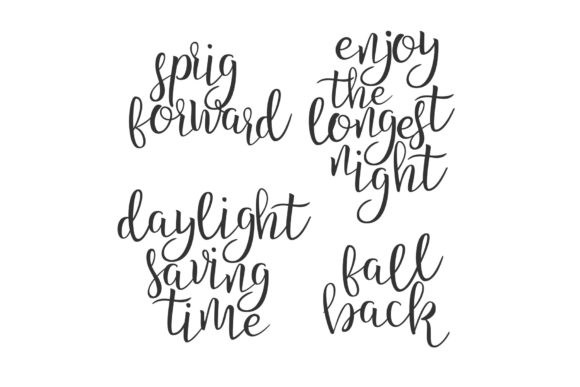
Пошук відповідних елементів дизайну може бути складним, але Modern Calligraphy Ink of Word Daylight пропонує виняткову колекцію, яка миттєво покращить вашу роботу.
Створений з високою точністю, Modern Calligraphy Ink of Word Daylight забезпечує чисті вектори, плавну типографіку та комерційну ліцензію для вашого спокою.
Незалежно від того, чи створюєте ви продукти POD (друк на вимогу), весільні запрошення або графіку для соціальних мереж, Modern Calligraphy Ink of Word Daylight стане ідеальним вибором.